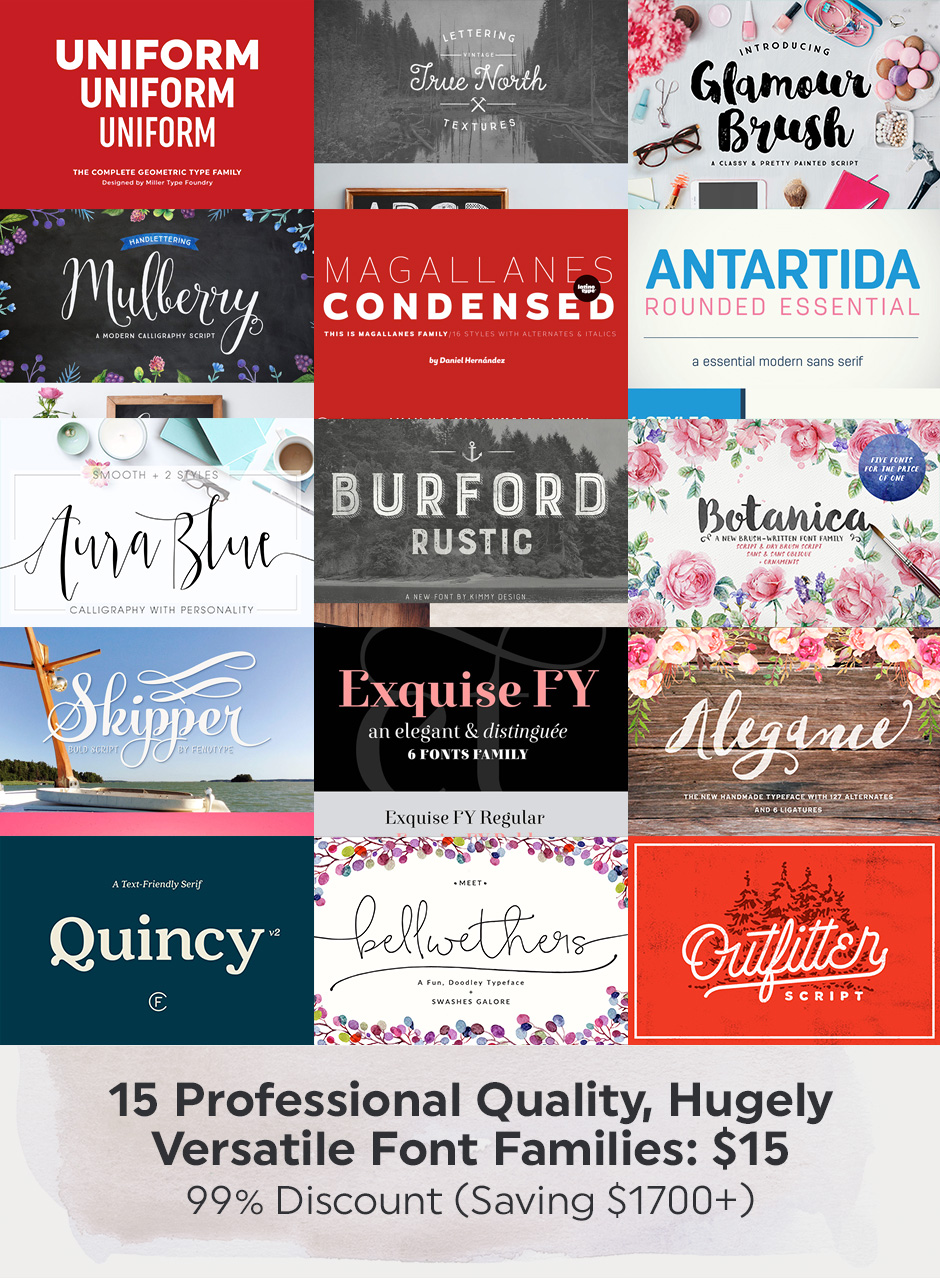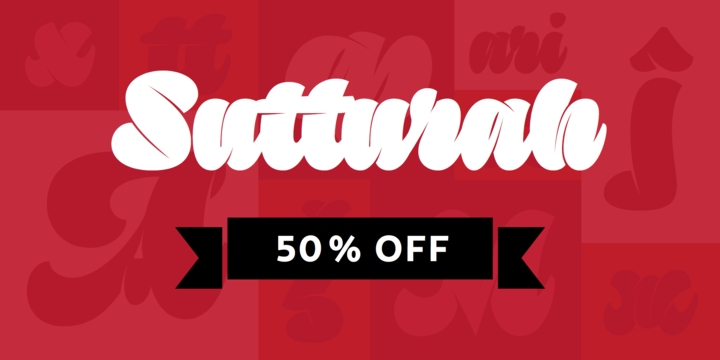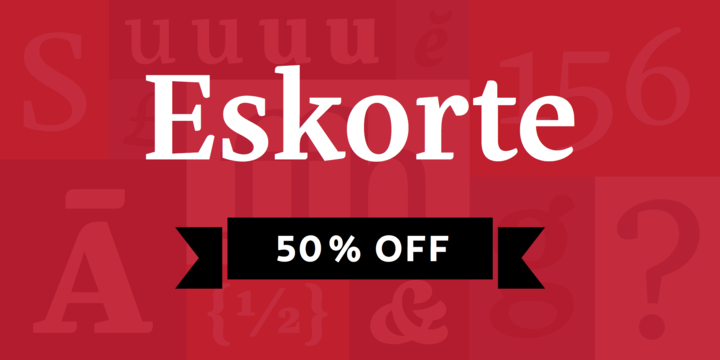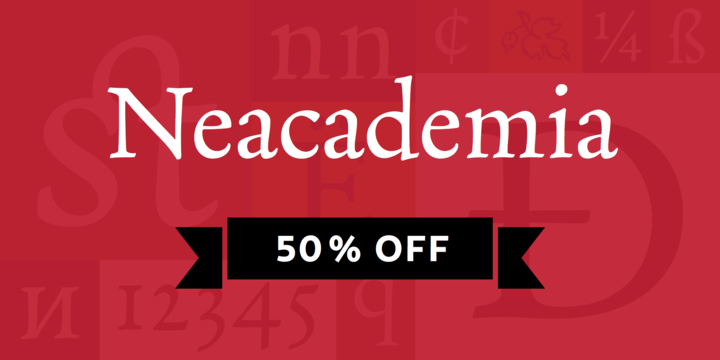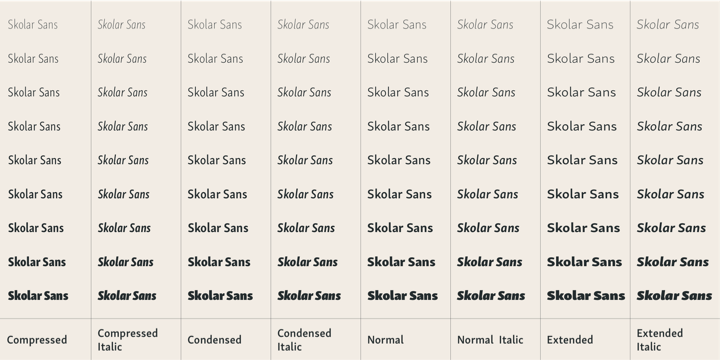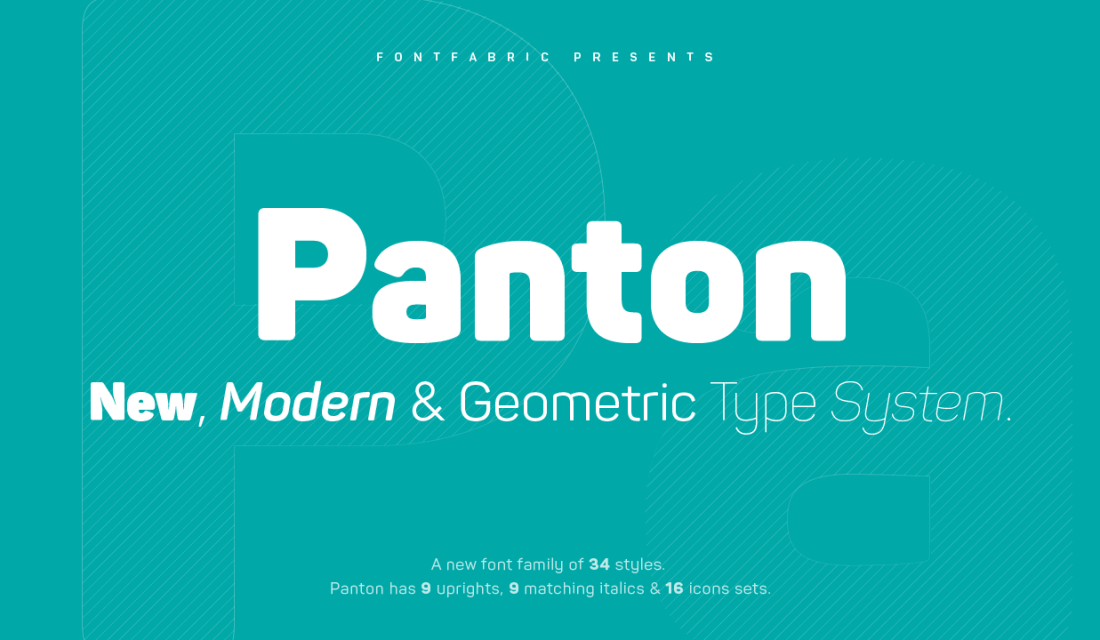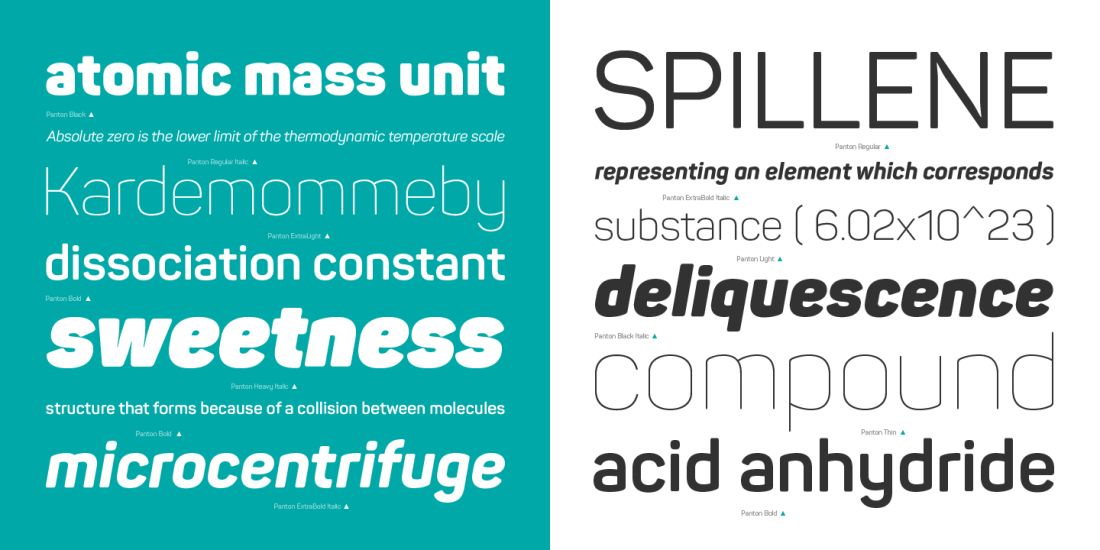
Neun Schnitte jeweils aufrecht und kursiv plus 16 Icon-Fonts.
Ich mag ja die normale Magallanes (mit ihrem ungewöhnlichen kleinen a) gerne, insofern würde mich die condensed schon reizen. Zumal das Magallanes-Condensed-Paket bei MyFonts 256,99 € kostet … Ist das beim von Dir verlinkten Angebot eine irgendwie abgespecke Variante?
Aber mir graust davor, mir im Schlepptau einen Sack halbgarer Scriptfonts an Bord zu holen – vermutlich auch noch überwiegend ohne ß … Müsste man mal genau prüfen.
Ich mag ja die normale Magallanes (mit ihrem ungewöhnlichen kleinen a) gerne, insofern würde mich die condensed schon reizen. […] Aber mir graust davor, mir im Schlepptau einen Sack halbgarer Scriptfonts an Bord zu holen – vermutlich auch noch überwiegend ohne ß … Müsste man mal genau prüfen.
Lach! Ganz genauso geht’s mir auch.  :gimmifive: Aber hattest Du Dir damals nicht die Magallanes Condensed schon besorgt?
Ist das beim von Dir verlinkten Angebot eine irgendwie abgespecke Variante?
Sieht nicht so aus:
It comes with 8 styles, from Ultra Light to Black, each with its true italics.
Also alle 16 Schnitte sollten enthalten sein. Nur die Antartida ist abgespeckt.
Aber hattest Du Dir damals nicht die Magallanes Condensed schon besorgt?
Nee, ich habe bislang nur die normale Magallanes.
Also alle 16 Schnitte sollten enthalten sein …
Sag mal, … Miller Type Foundry. Die ist in dem Paket mit der Uniform vertreten. Erstens finde ich die immens dicht an der DIN, oder? Und zweitens: Was ist von der Foundry zu halten? Mir scheint, die machen ansonsten eher so lala Schriften. Oder tue ich da jetzt Foundry und Schrift Unrecht?
Mir kommt die Uniform inkonsequent konzipiert (etwas von der Gotham, etwas von der DIN, …) und unsauber gezeichnet vor. Auch ein Grund, warum ich das mit den Attributen gesagt habe – mit “Quality” verbinde ich etwas anderes. Aber Du bekommst die Magallanes Condensed für 15 Dollar – ich weiß nicht, ob das so schnell wieder der Fall sein wird. ;-) Die Botanica und True North sind ja auch ganz reizend.
Nachtrag: Huuuch, ich habe die Magallanes condensed ja doch schon …! Warum weißt denn Du das und ich nicht?  :-? Na ja – jetzt brauche ich zumindest das neue Paket nicht kaufen. Gerade noch rechtzeitig gemerkt … :puh!:
Wow! Seit heute gibt es die Skolar Sans bei Myfonts und ein Schnitt kostet (Normalpreis!) nur 35,– Euro. Für eine mehrfach ausgezeichnete und hinsichtlich Schnittvarianten und Zeichenumfang bemerkenswert ausgebaute Schrift ganz schön moderat!
Die folgenden drei (ebenfalls ausgezeichneten) Schriften von Rosetta gibt es momentan für den halben Preis:
Sieht ja schick aus – aber wie heißt denn die Schrift bloß!? Ich kann das nicht lesen … :-?
Nachtrag: Aaaah: Sutturah heißt sie. Das sollten die aber wirklich dazuschreiben.  ;-)
Wow! Seit heute gibt es die Skolar Sans bei Myfonts und ein Schnitt kostet (Normalpreis!) nur 35,– Euro.